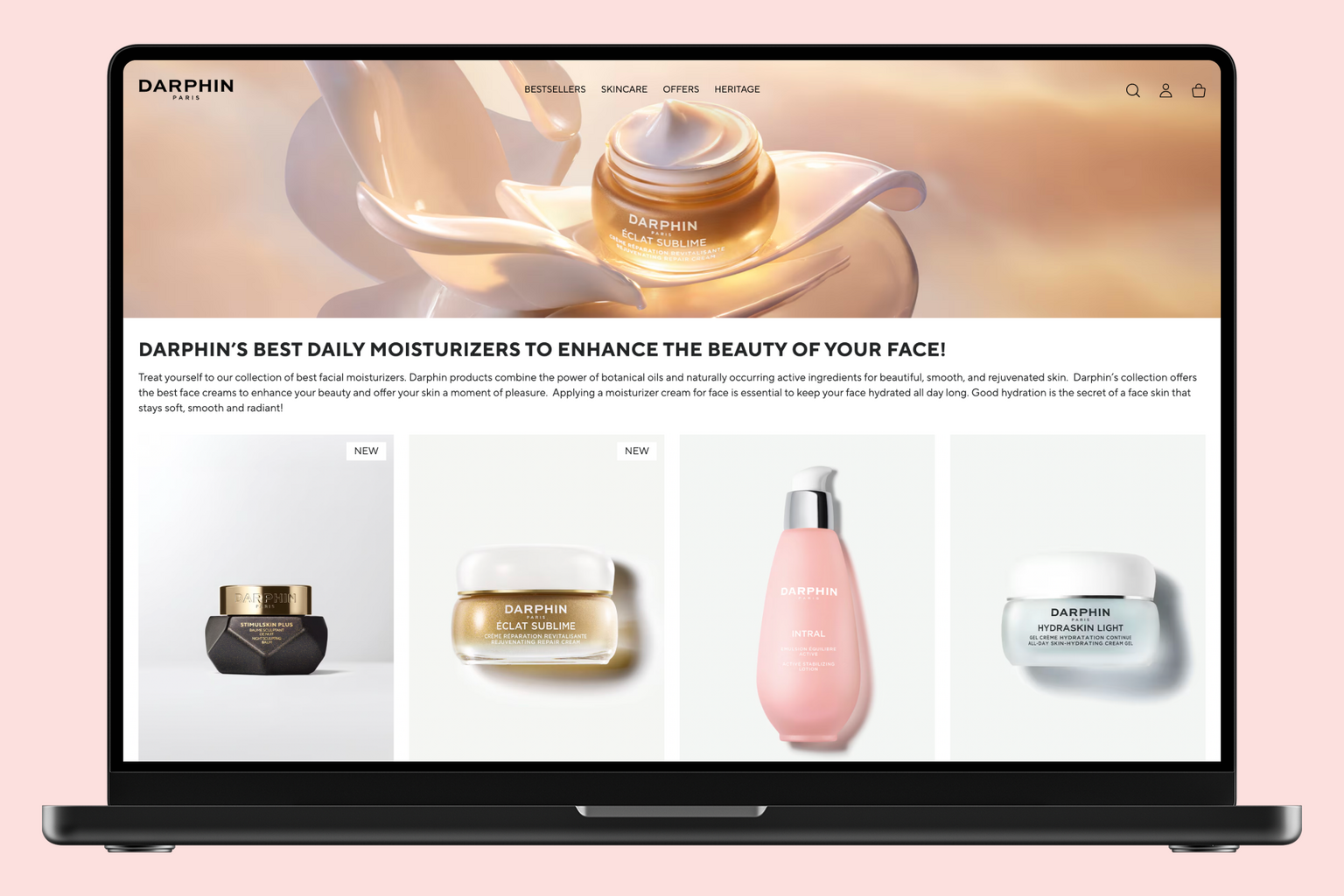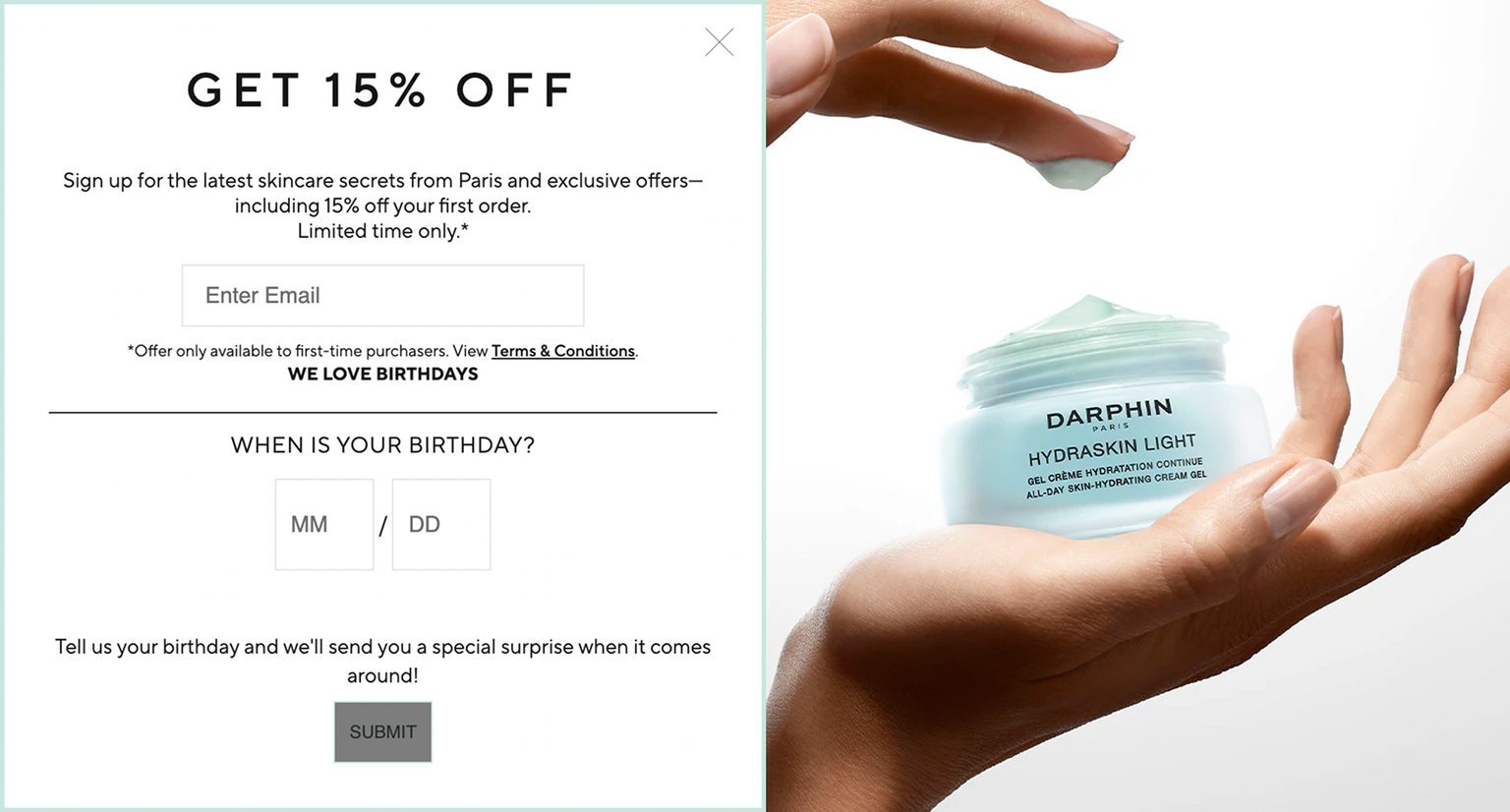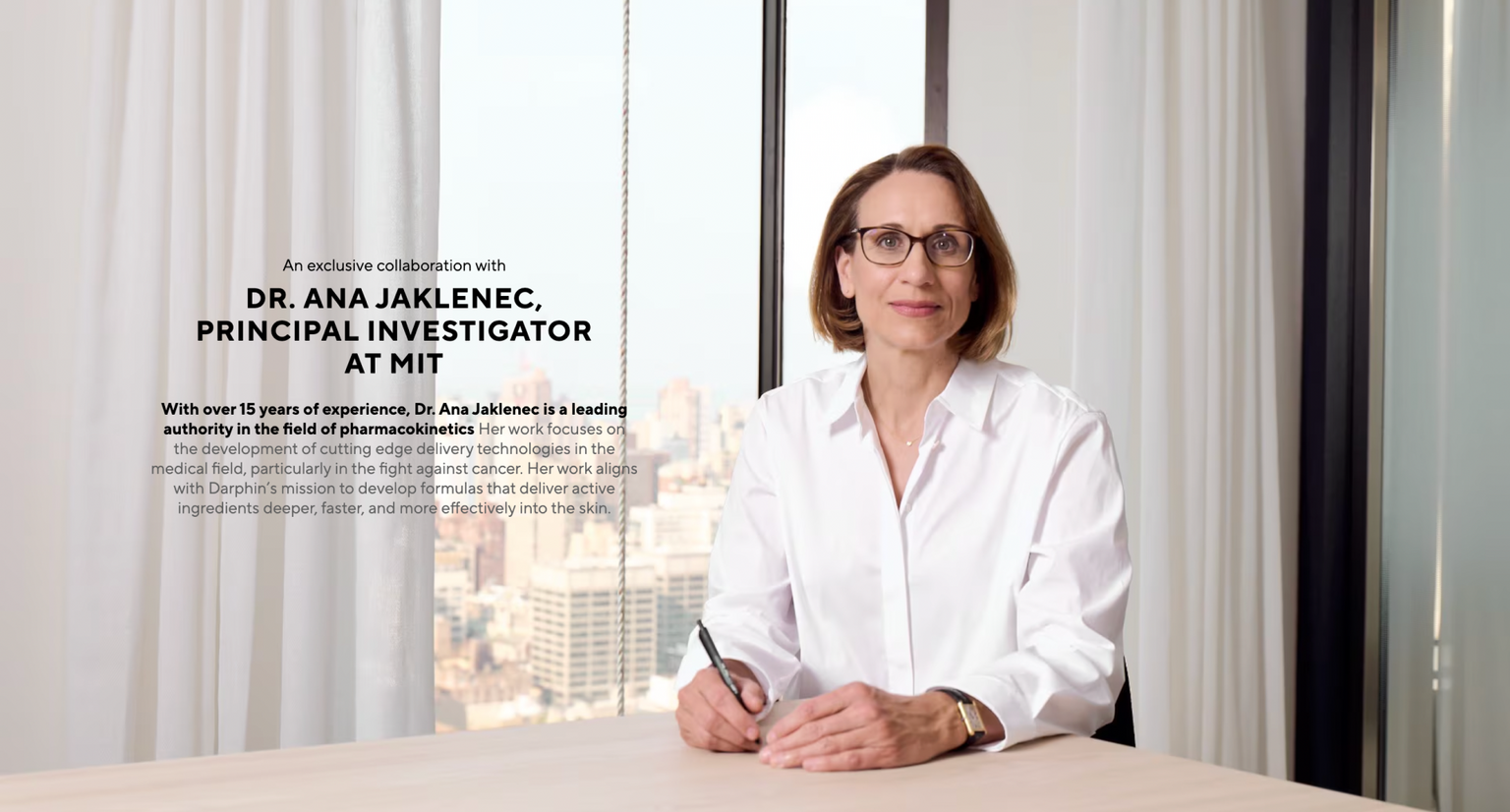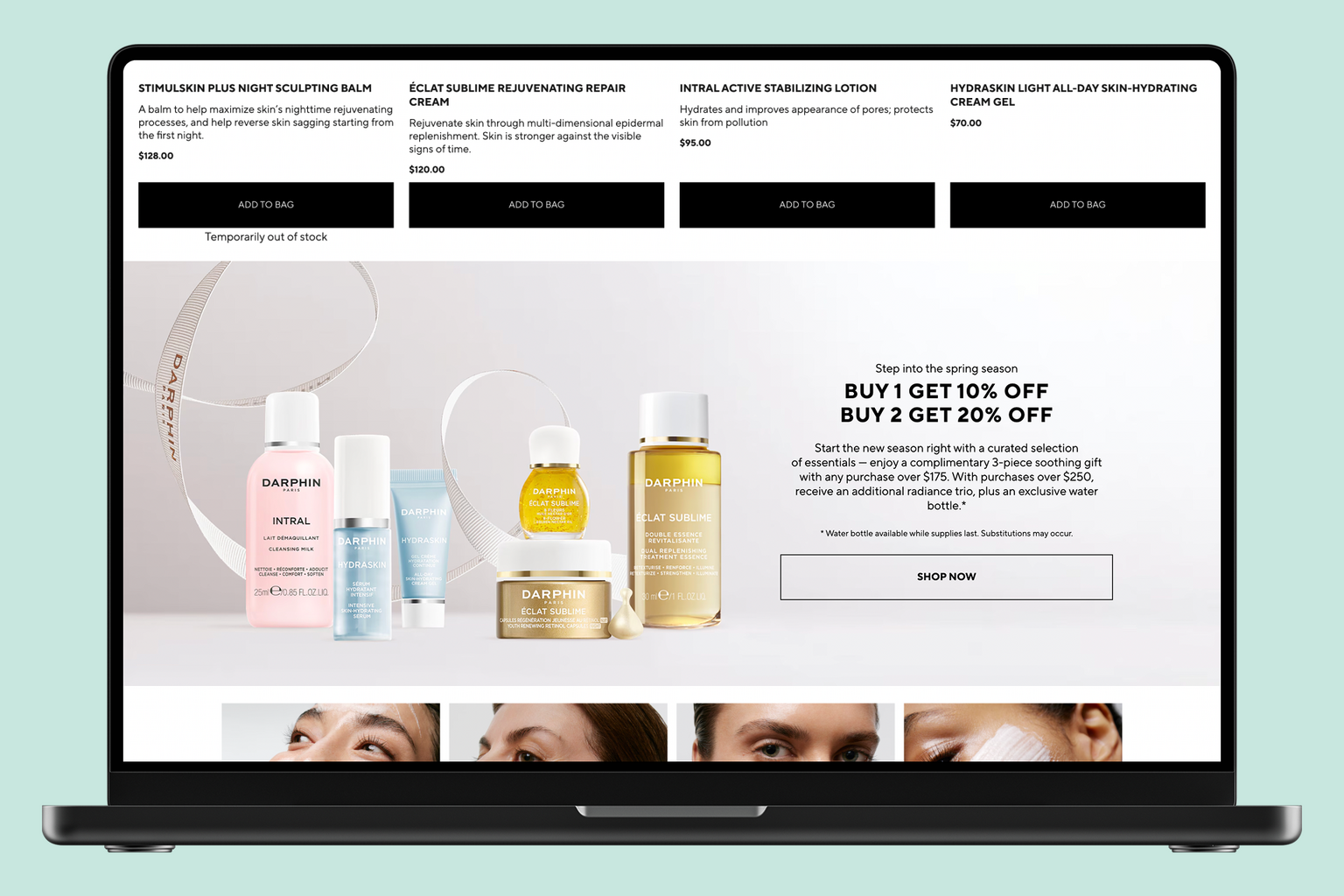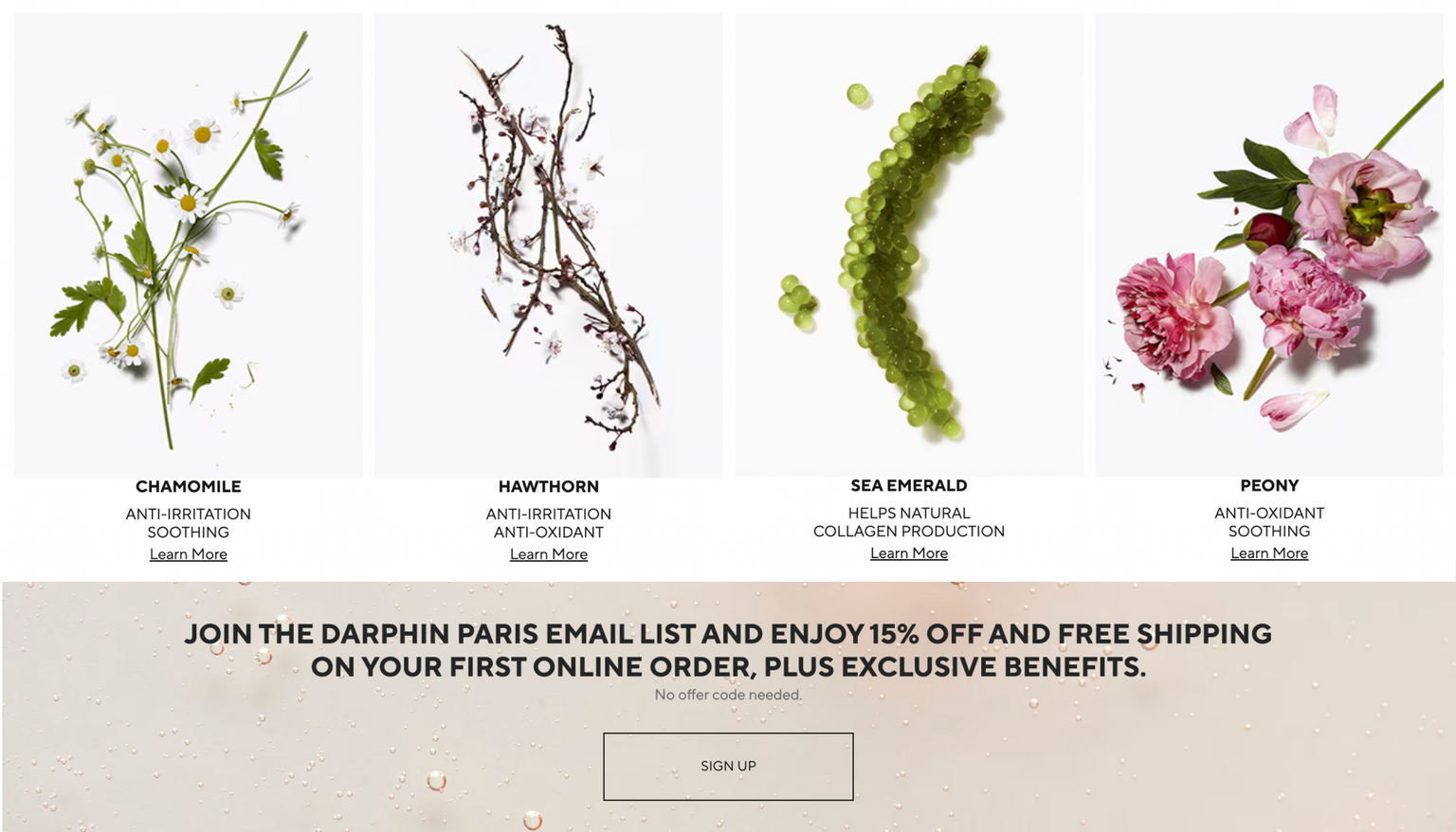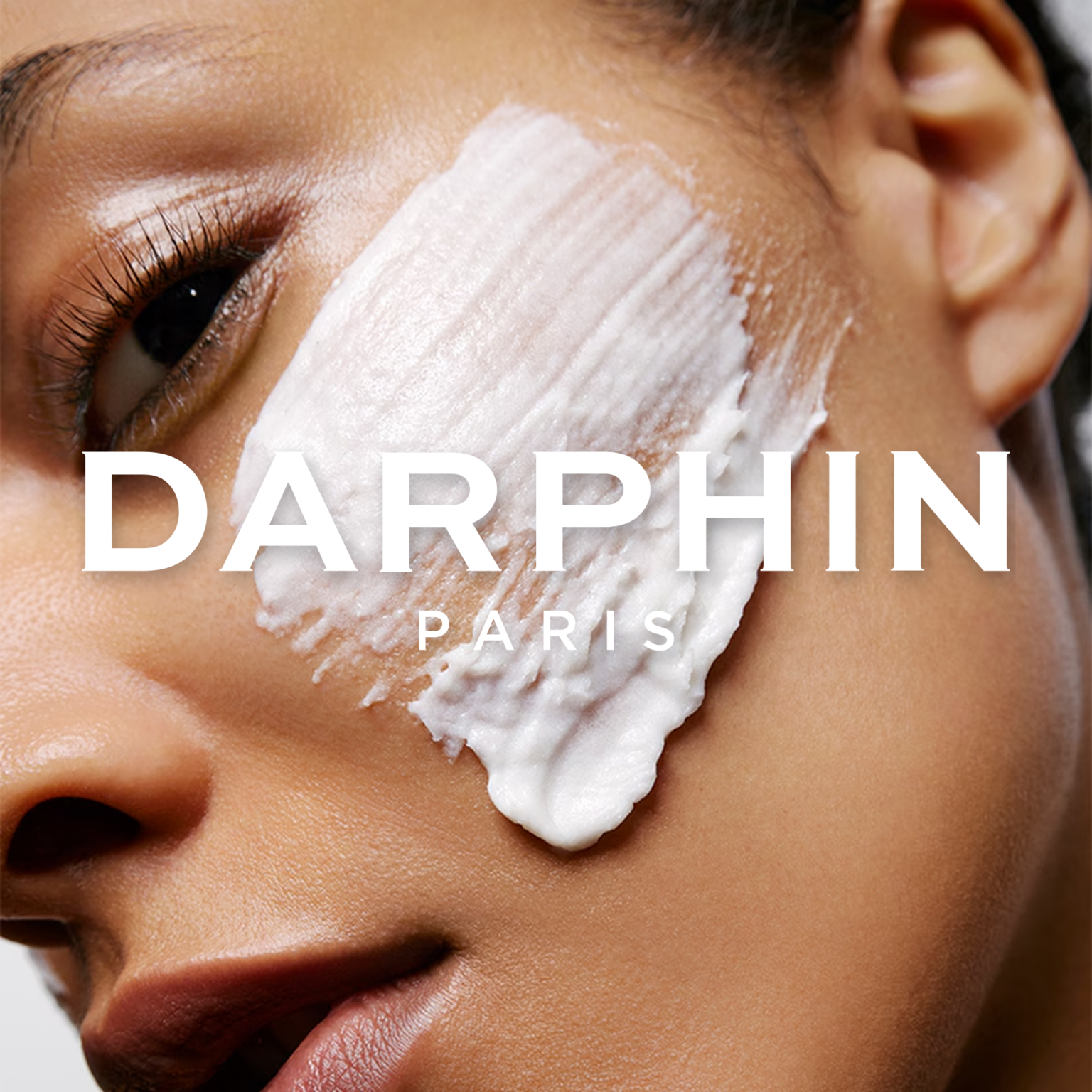
ТТ Нормс Про (TT Norms® Pro) используется в фирменном стиле компании DARPHIN.
Darphin — это французский люксовый бренд уходовой косметики. Основанный в 1958 году, он славится тем, что сочетает инновационные формулы, научное наследие и растительные компоненты. ТТ Нормс Про помог подчеркнуть акцент на высокотехнологичном подходе, не отодвигая на второй план тему богатой истории компании.